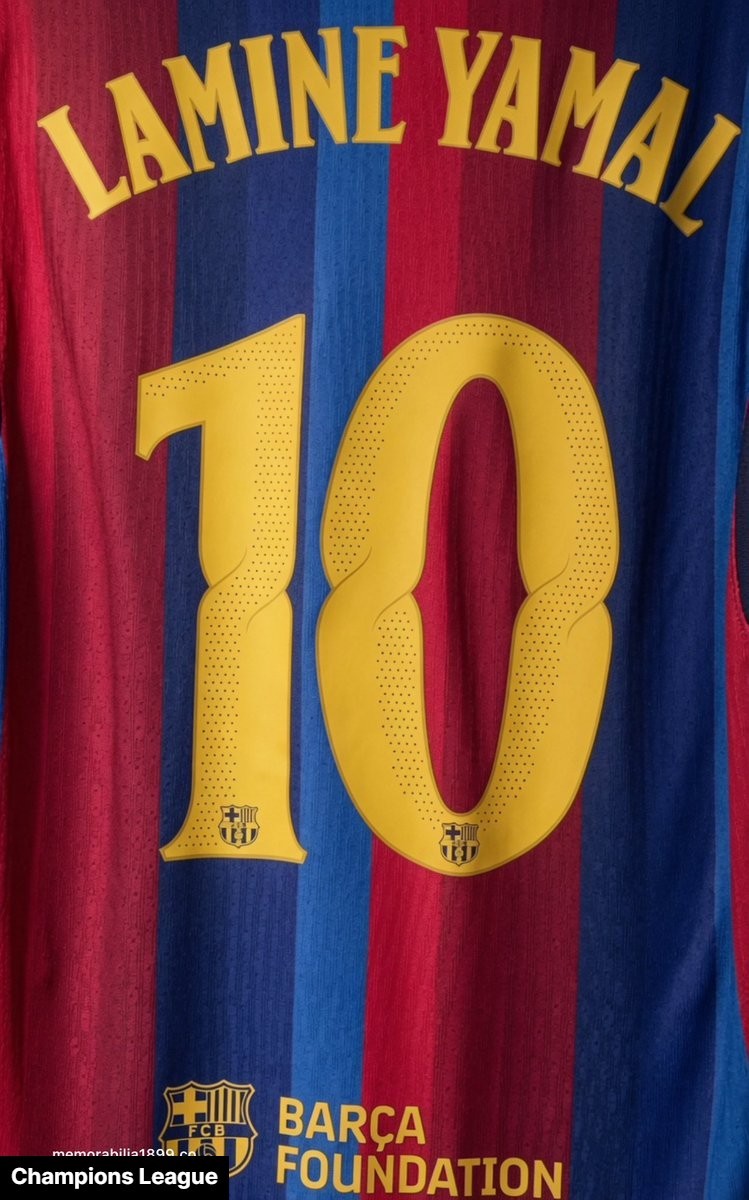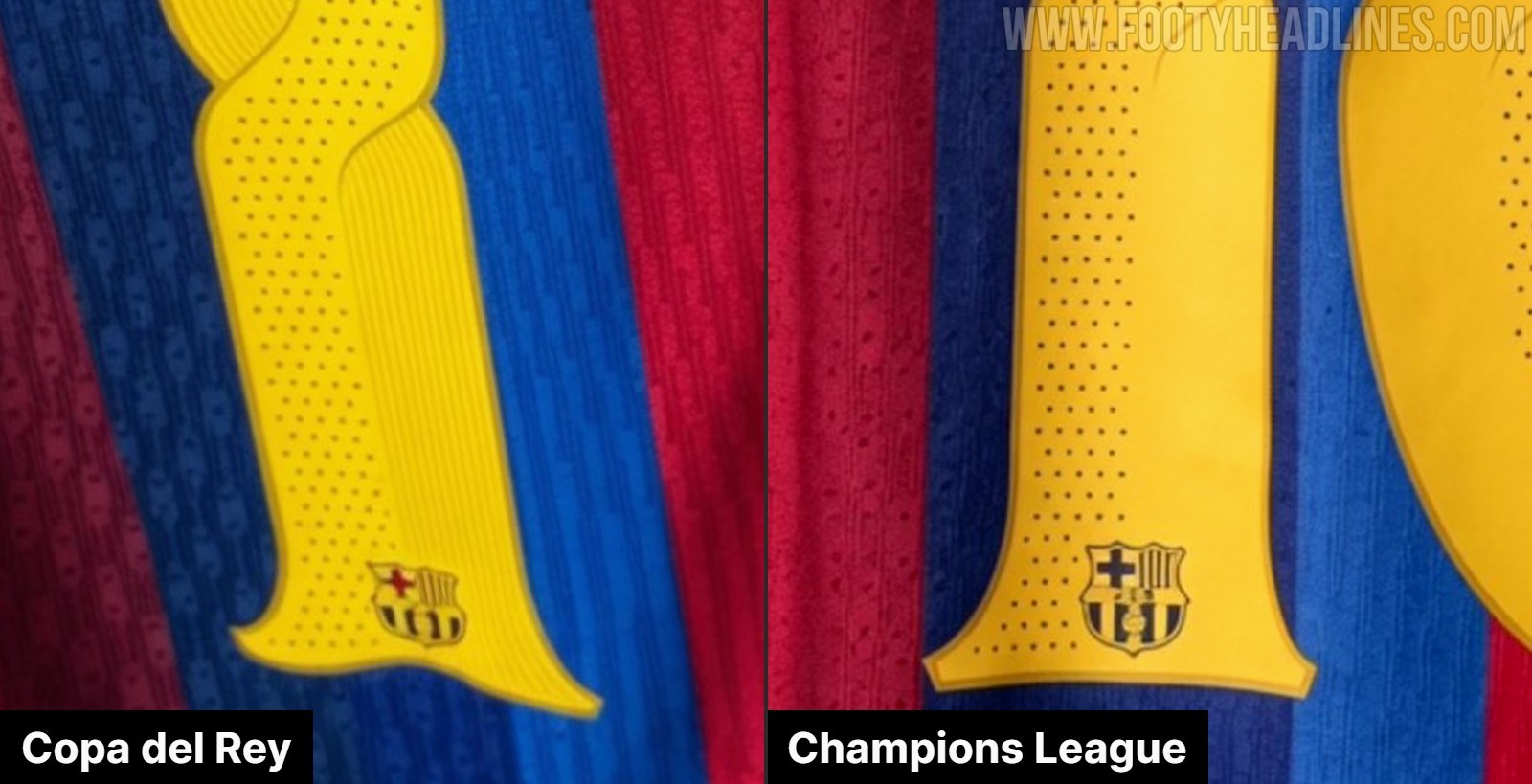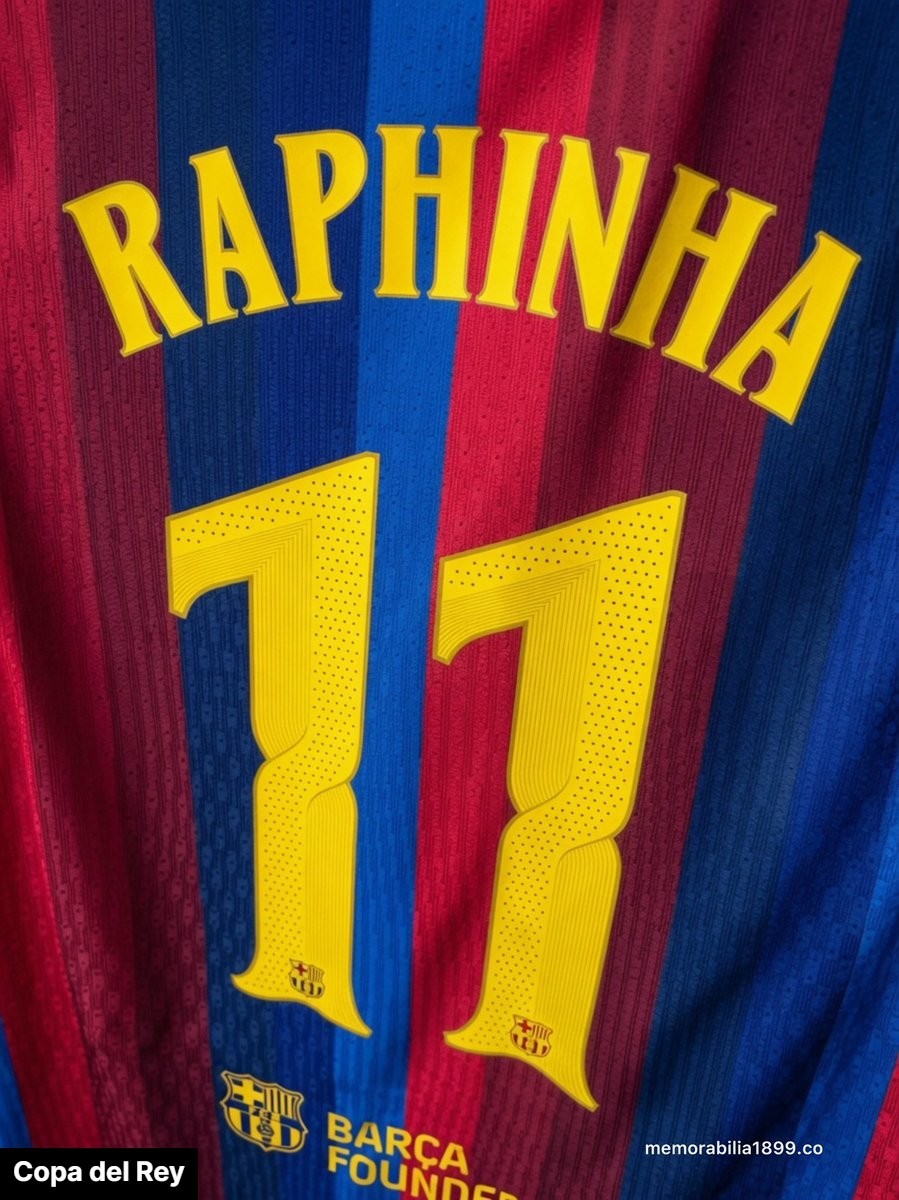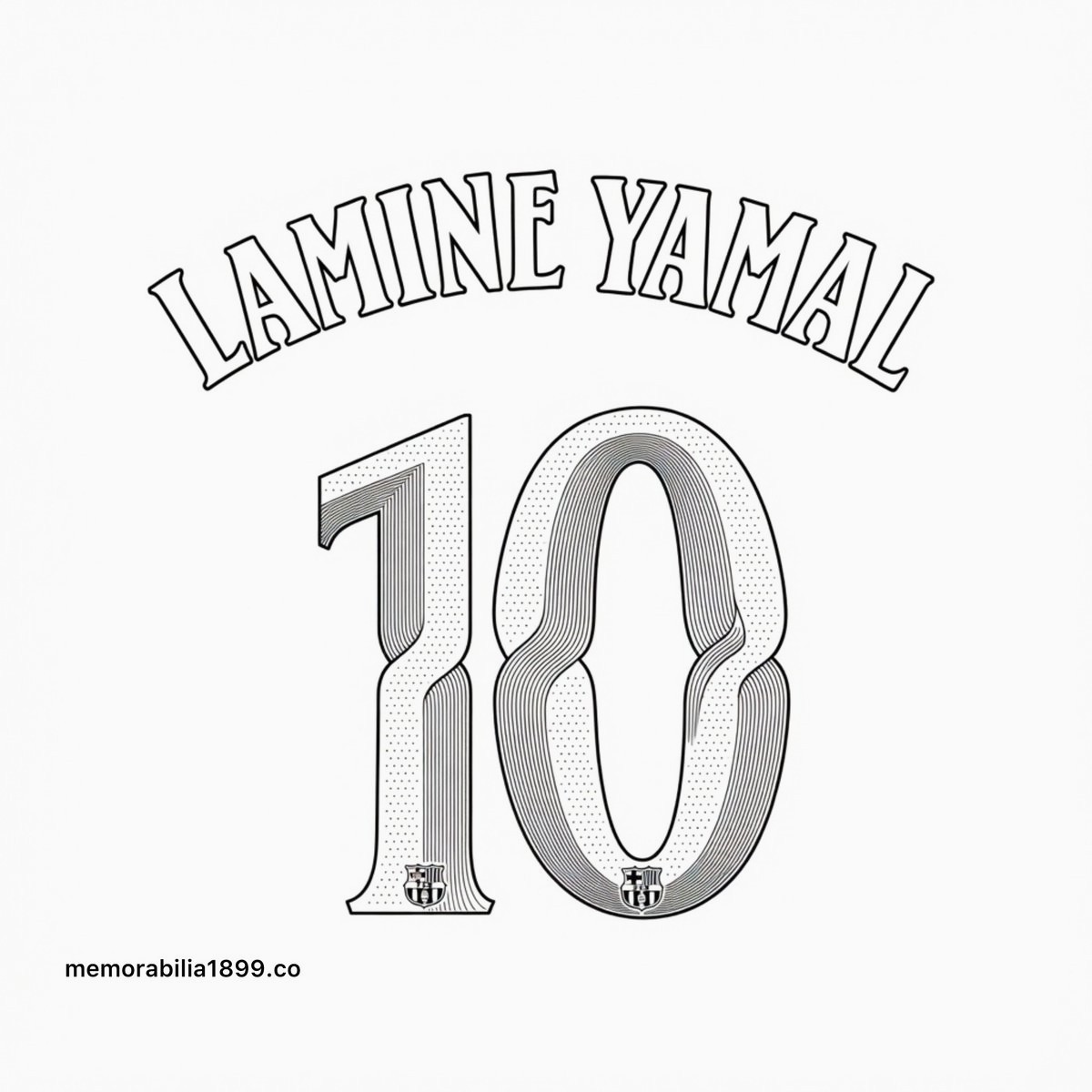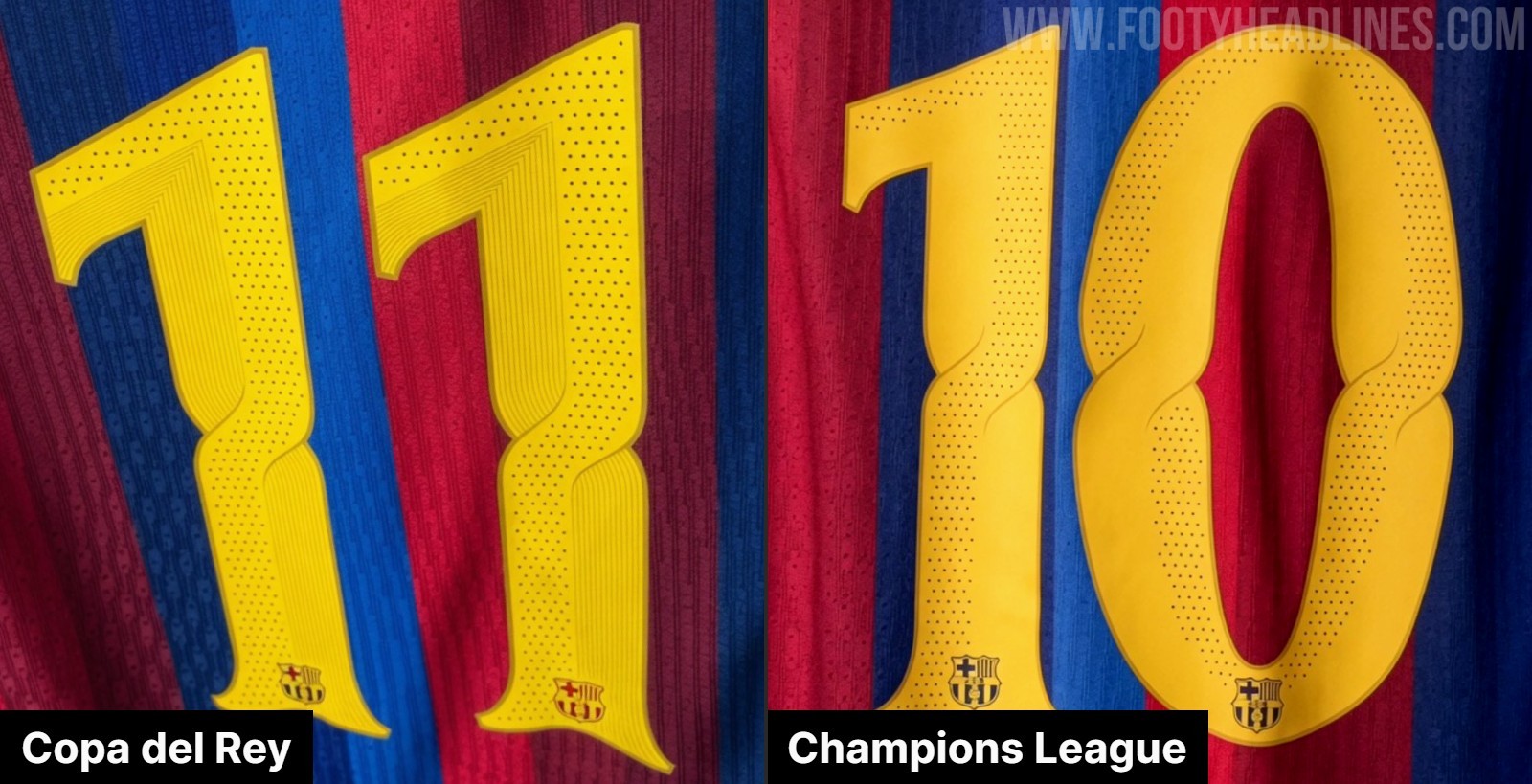
Die Schriftart des FC Barcelona 26-27 Champions-League-Trikots weist aufgrund der UEFA-Trikotvorschriften geringfügige Eigenschaften auf
• Neue Trikotschriftart für FC Barcelona 26-27: Der FC Barcelona wird in der Saison 2026/27 eine brandneue, eigens entworfene Trikotschriftart für Pokal- und Champions-League-Spiele verwenden, die vom „Modernisme Català“ inspiriert ist und fließende Kanten aufweist.
• Unterschiede zwischen Pokal- und Champions-League-Version: Aufgrund der strengen UEFA-Vorschriften weist die Schriftart geringfügige Unterschiede auf, wobei die nationale Pokalversion dezente integrierte Streifen hat, die Champions-League-Version jedoch durchgehende Zahlen ohne innere Linien besitzt.
• Exklusivität und Nichtverwendung in La Liga: Diese maßgeschneiderte Schriftart ist ausschließlich für Pokal- und Europapokalspiele reserviert, da der Verein in der La Liga weiterhin die standardisierte Liga-Schriftart nutzen muss und sie dort nicht verwenden darf.
Der FC Barcelona wird bei seinen Freundschaftsspielen der Saison 2026/27 eine brandneue, eigens entworfene Schriftart verwenden. Dank des Barcelona-Insider-Experten @memorabilia1899 sehen wir, dass es geringfügige spezifische Unterschiede zwischen den Versionen für die Copa del Rey und die UEFA Champions League gibt.
FC Barcelona 26-27: Schriftart für Pokal vs. Champions League
Die neue Schriftart für das Trikot des FC Barcelona 2026-27 hat die Eigenschaft fließende Kanten und Kurven zu haben und ist stark vom „Modernisme Català“ inspiriert, einer berühmten katalanischen Kunst- und Literaturbewegung. Dieser Einfluss verleiht den Namen und Nummern ein unverwechselbar künstlerisches und elegantes Aussehen und hebt sie von traditionelleren, kantigen Sportschriften ab.
Obwohl das Grunddesign der Schriftart einheitlich ist, gibt es einen deutlichen Unterschied zwischen den Versionen, die bei den heimischen Pokalwettbewerben und in der UEFA Champions League getragen werden. Die Standard-Pokal-Schriftart, die für den Einsatz in der Copa del Rey und der Supercopa de España vorgesehen ist, hat als Eigenschaft dezente, in die Zahlen integrierte Streifen.
Die strengen Ausrüstungsvorschriften der UEFA lassen diese dekorativen Streifen im Inneren der Zahlen jedoch nicht zu. Daher wird die Champions-League-Version der Schriftart „Barcelona 26-27“ durchgehende Zahlen ohne innere Linien aufweisen, um die Einhaltung der europäischen Wettbewerbsregeln zu gewährleisten und gleichzeitig die fließende, vom Modernisme inspirierte Silhouette beizubehalten.
Wie üblich wird der FC Barcelona diese maßgeschneiderte Schriftart in der La Liga nicht verwenden dürfen. Der Verein wird weiterhin die ligaweit standardisierte Schriftart für alle Spiele der spanischen Erstliga nutzen, was bedeutet, dass dieses neue künstlerische Design ausschließlich für Pokal- und Europapokalspiele reserviert ist.